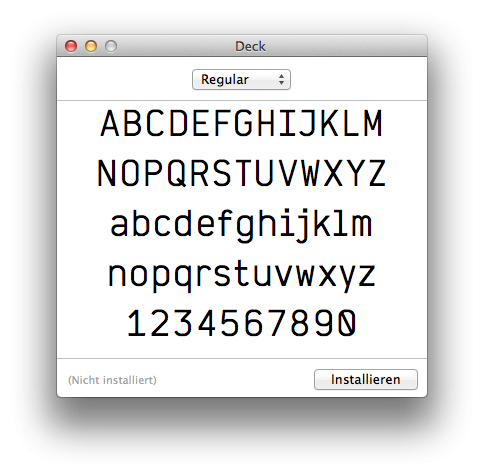
Alternative für Deck (Webfont)
Die Anonymous von Mark Simonson ist auch eine Schrift mit dicktengleichen Zeichen. Es gibt sie bei bei Google Fonts (SIL Open Font License, 1.1). Sie sollte also als Webfont funktionieren. Leider kommt sie der Deck nicht annähernd nah (außer dass beide sogenannte Typewriter-Fonts sind).